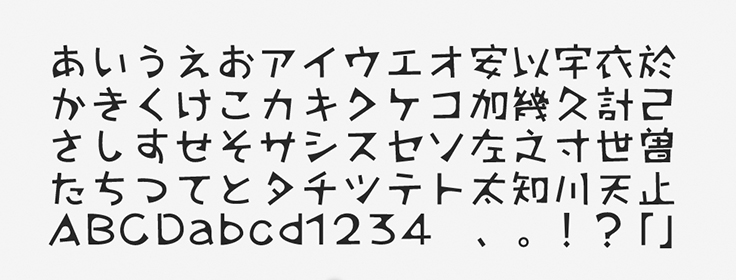
「タカモダン」について
タカハンドでも有名な、たかデザインプロダクション(高原新一書体デザイン室)が手掛ける「タカ書体」の1つで、2014年にモリサワでの提供が開始されました。同時リリースされたタカポッキが持つリズム感を踏襲しつつ、線画が交差する部分に墨だまりのような黒みを持たせています。
「タカモダン」の特徴
墨だまりのような黒みの効果により、タカポッキと比べてレトロモダンな雰囲気が強調されているデザインフォントです。また、タカポッキは画線の太さが一定ですが、タカモダンは文字にメリハリがあり、個性的な印象です。どこか懐かしくもあり、新しくもあるような独特なイメージのフォントと言えるでしょう。
墨だまりの位置や角度や太さは、文字に合わせて個別に調整されています。そのため、どの文字を組み合わせても最適なバランスで見せられるフォントです。
レトロモダンな印象の強いタカモダンですが、動きがあって楽しいイメージを表現しやすいことも魅力の1つです。作例では、文字ごとの角度などで動きに変化を加えてグラフィックも組み合わせながら勢いを強めました。楽しいイメージをさらに強調しています。